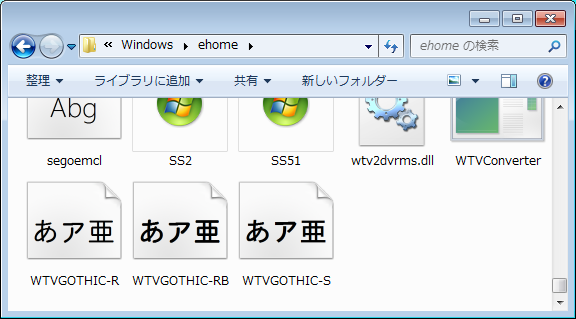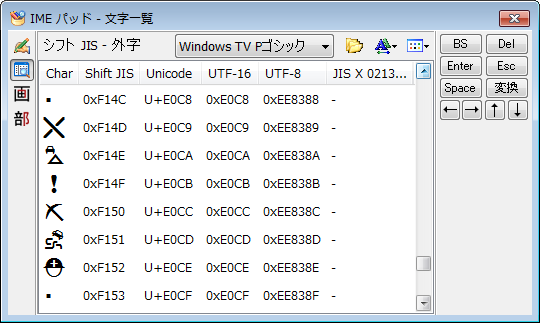
- Windows TV 丸ゴシック & Windows TV P丸ゴシック
- Windows TV 太丸ゴシック & Windows TV P太丸ゴシック
- Windows TV ゴシック & Windows TV Pゴシック
が入っていた。どれもバージョンは001.000、コピーライトは (c)2007 TypeBank Co., Ltd. となっている。IPAフォントと同じく、タイプバンク製らしい。
で、「TV ゴシック」の「TV」って何さ?というと、
こんな感じでデジタル放送用の記号類(ARIB外字)が入っているので、「TV ゴシック」ということらしい。これらの記号は「STD-B24 デジタル放送におけるデータ放送符号化方式と伝送方式」という規格で定められている。PDFの76ページあたりを参照。
Unicode にまだ収録されていない文字は、こんな感じでPUA/シフトJISの外字領域に割り当てられている。
これらの記号も既に2007年には “N3341 Japanese TV Symbols”(PDF)として ISO/IEC 10646 への収録が提案されていて、Amd. 6(PDF)あたりで追加される予定らしい。